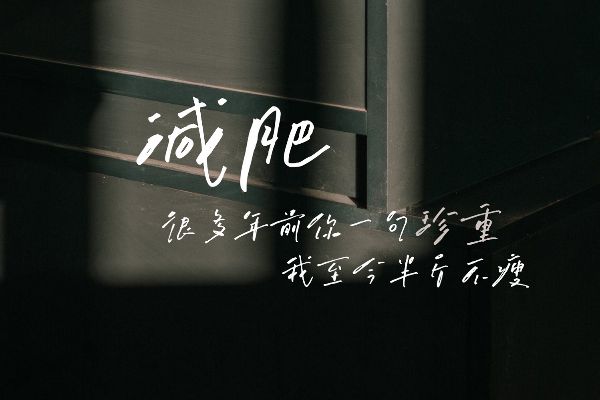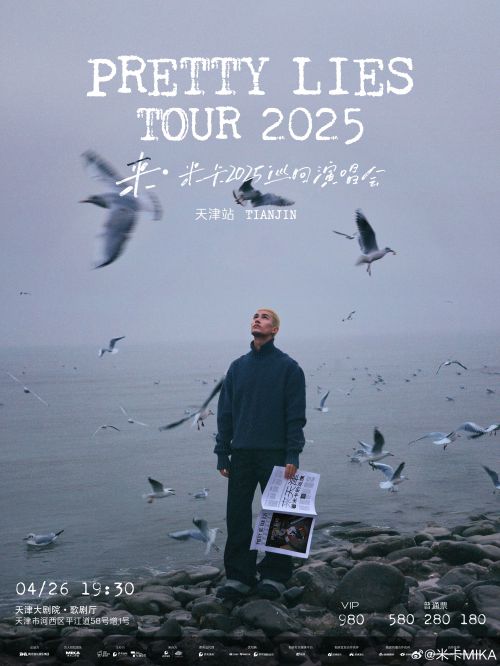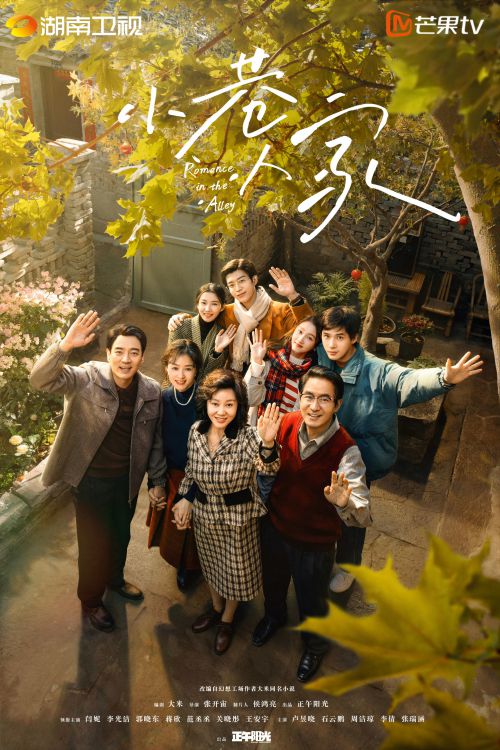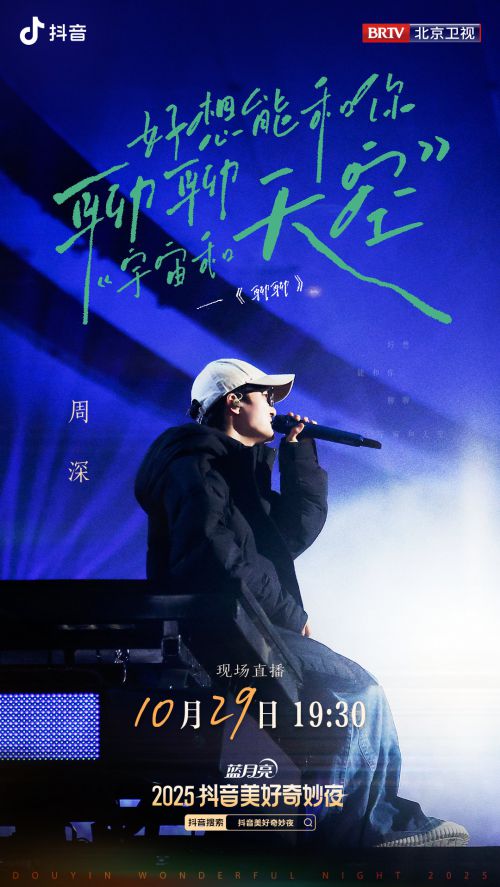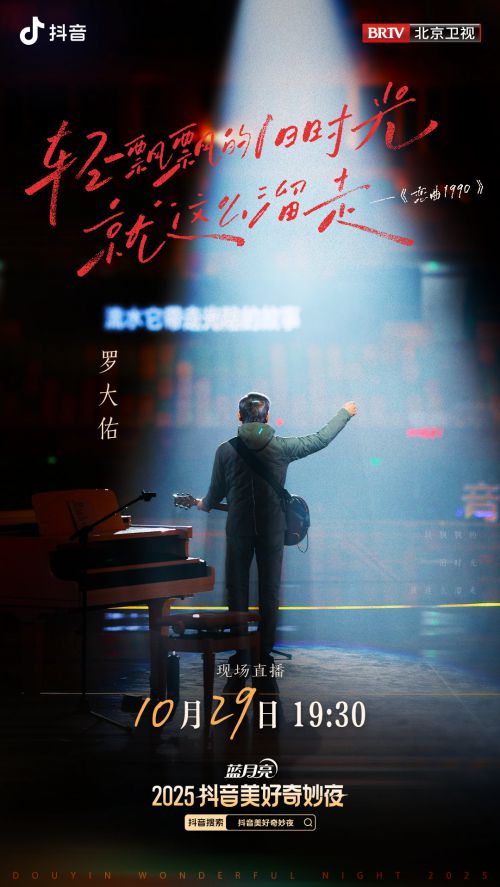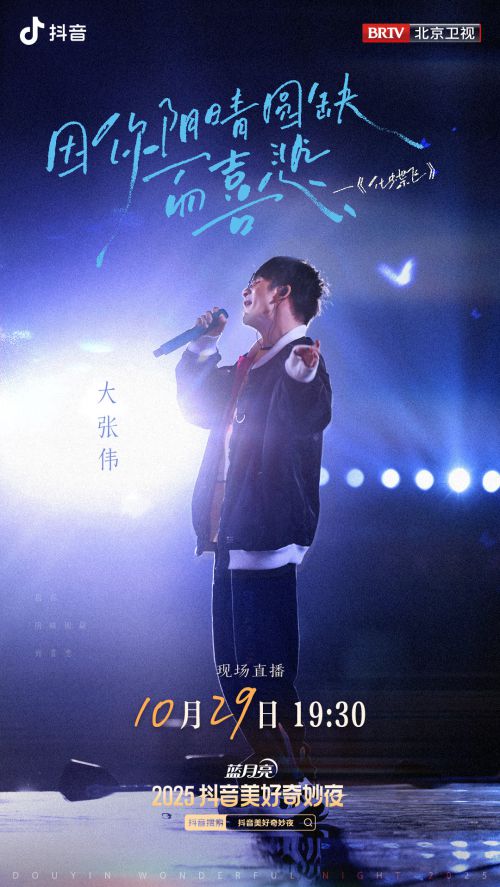
默陌心晴手写体
一款青春恣意的手写字体,字形结构舒展俏皮,呈倾斜的飞扬之态,书写节奏流畅轻快,点画疏密有致、粗细对比鲜明,笔触充分保留涂绘的肌理和质感,赋予字体轻盈快意的情绪色彩。
默陌
默陌是一名独立设计师,从事字体创意设计多年,目前已发布默陌水墨手迹系列、默陌硬笔手写体系列、默陌奇趣可爱手写系列等30余款字体字库作品,广泛应用于平媒、影视、手机端显示等场景。默陌字体字形多变,风格多元,坚持致力于传统书法意趣和现代手写个性的有机融合,创作出更多美好的原创手迹。